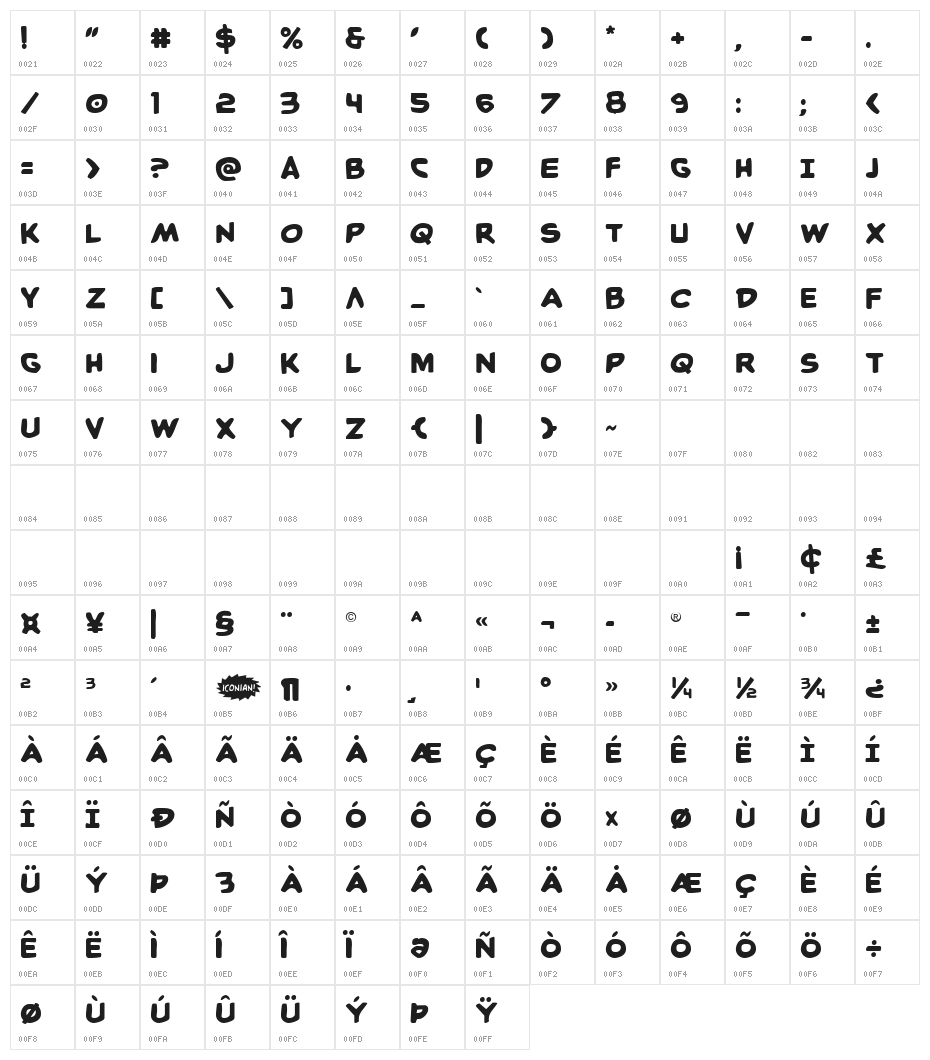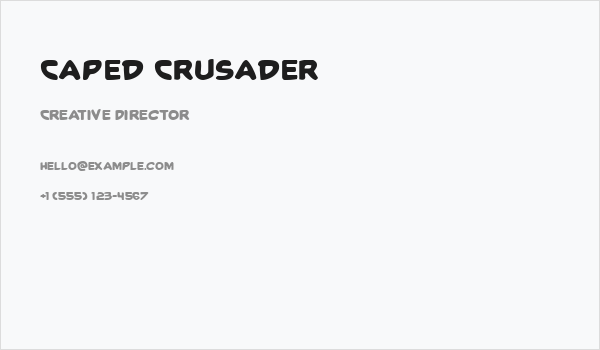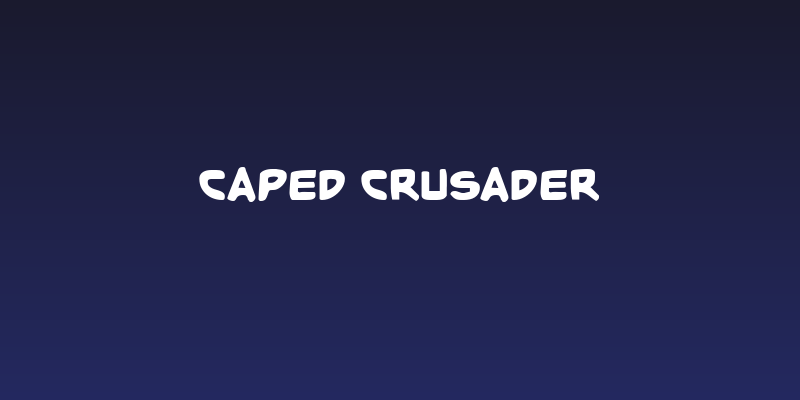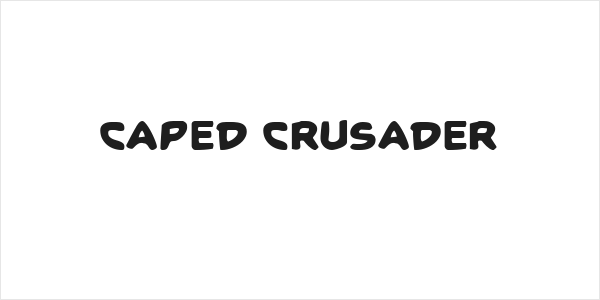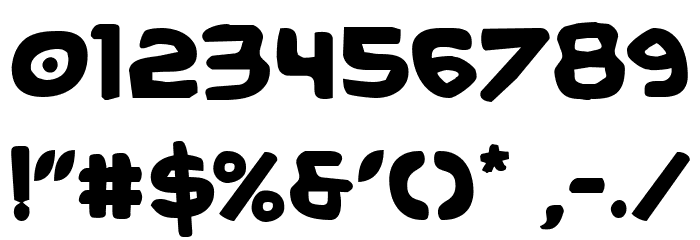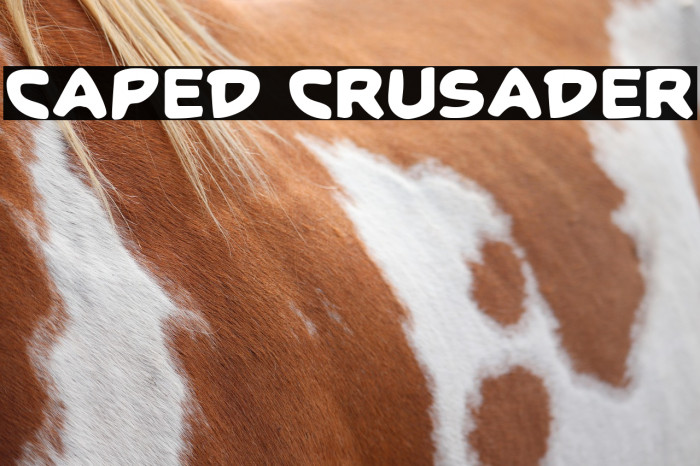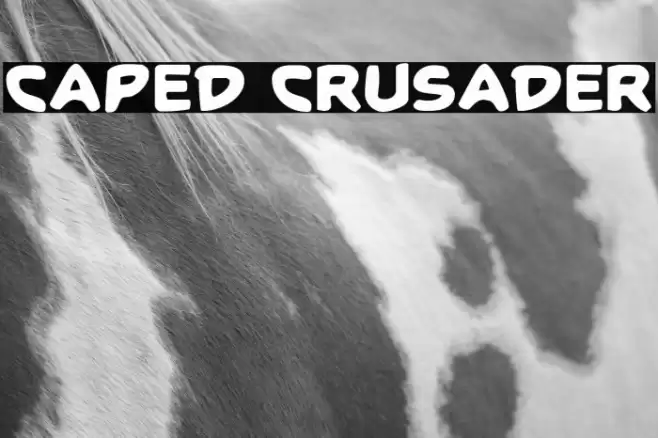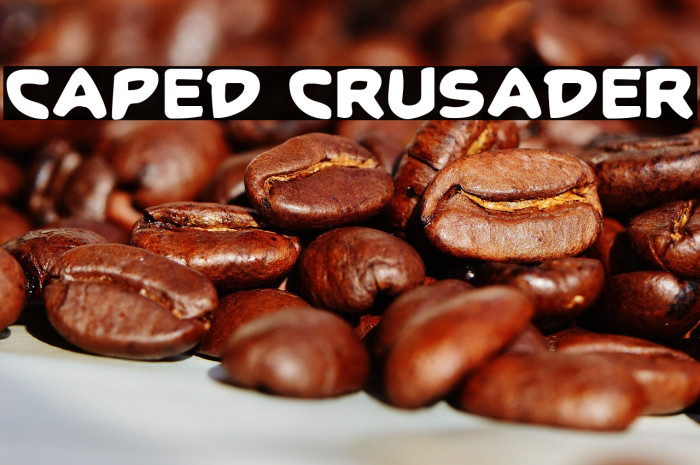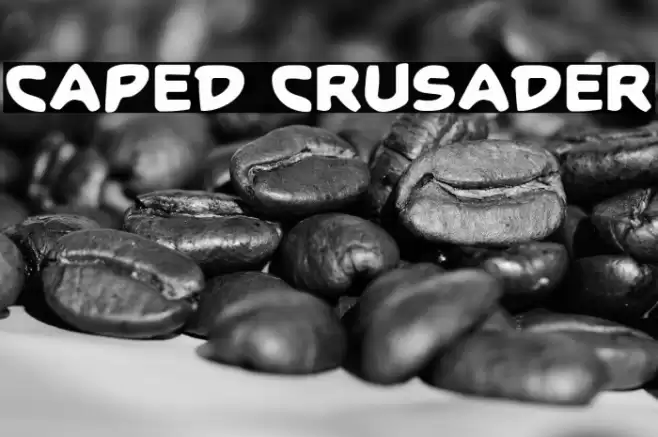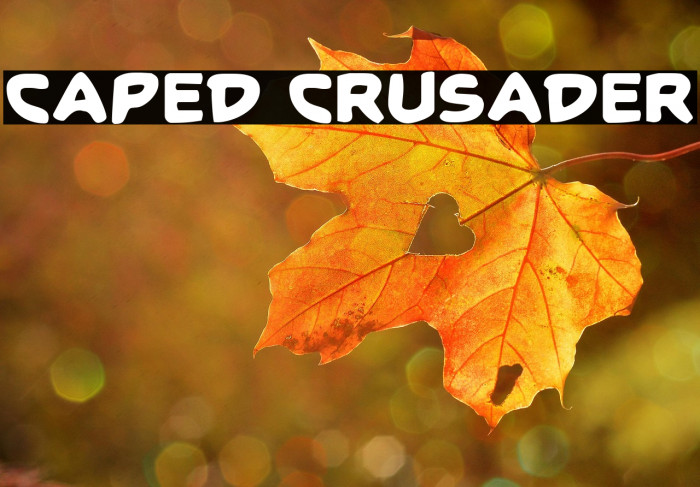
Caped Crusader Font
| Gesamtstil | Playful, Hand-drawn |
| Vorgeschlagene Projekte | Ideal for comic books, children's books, playful branding, and eye-catching posters. |